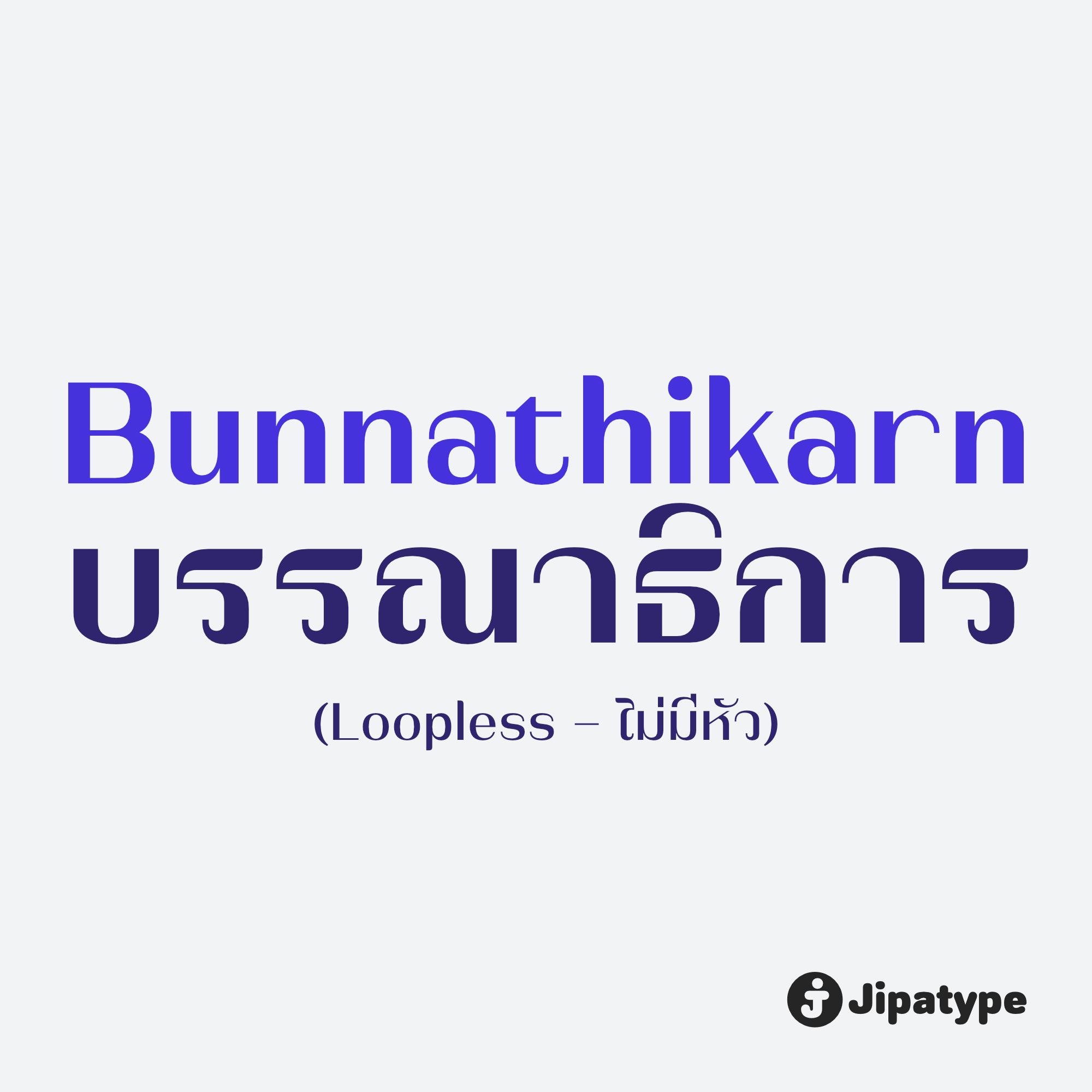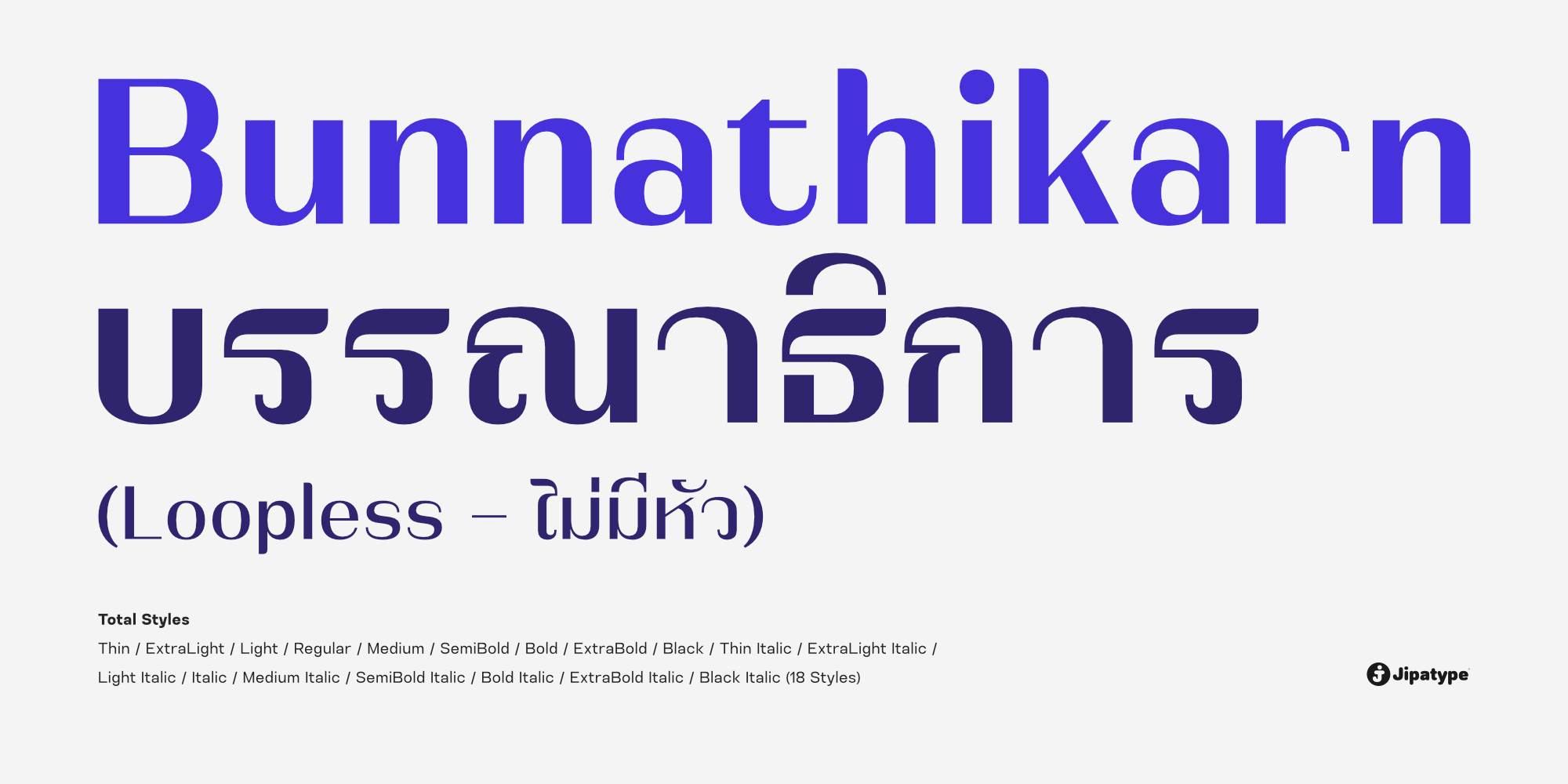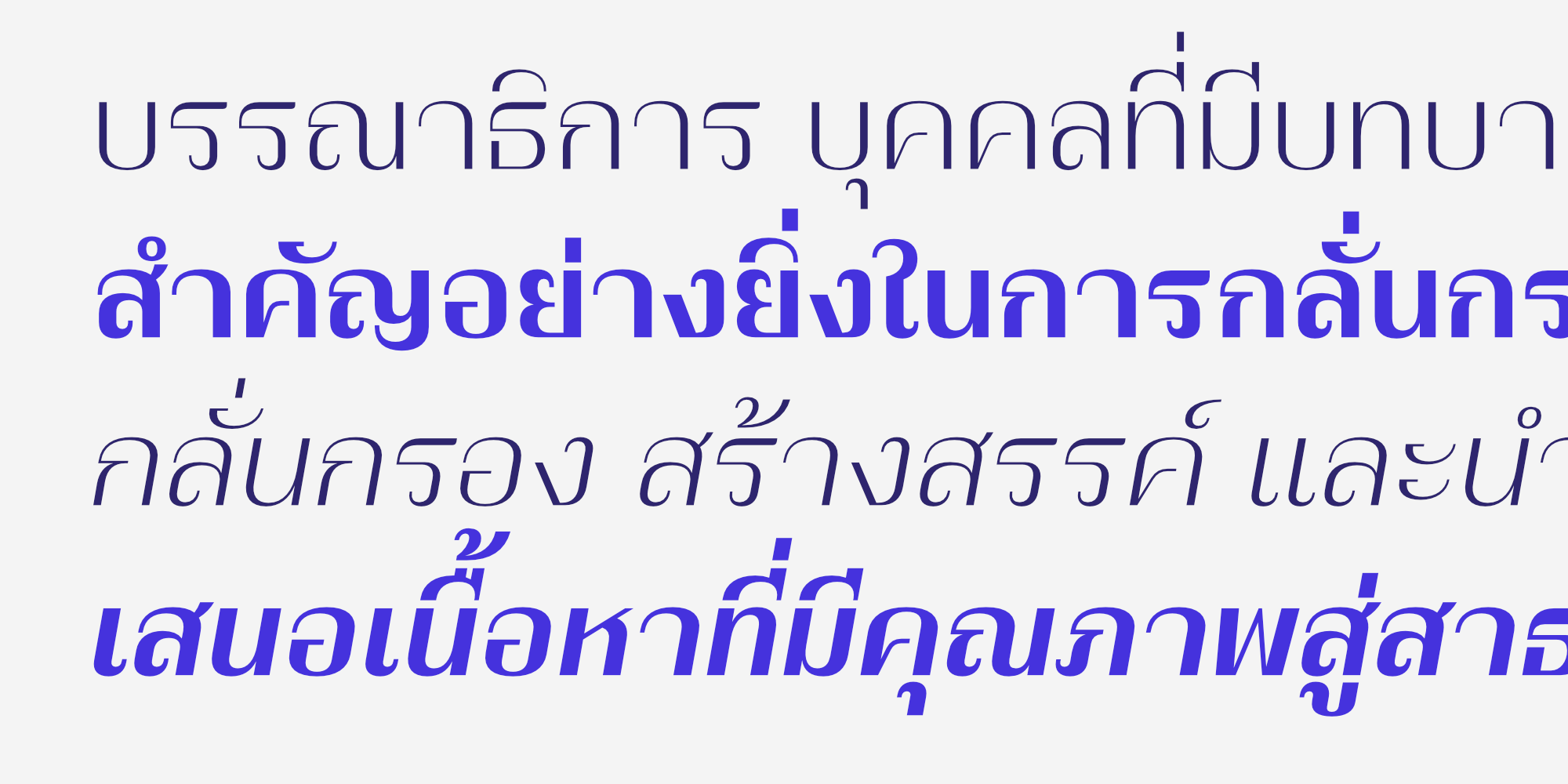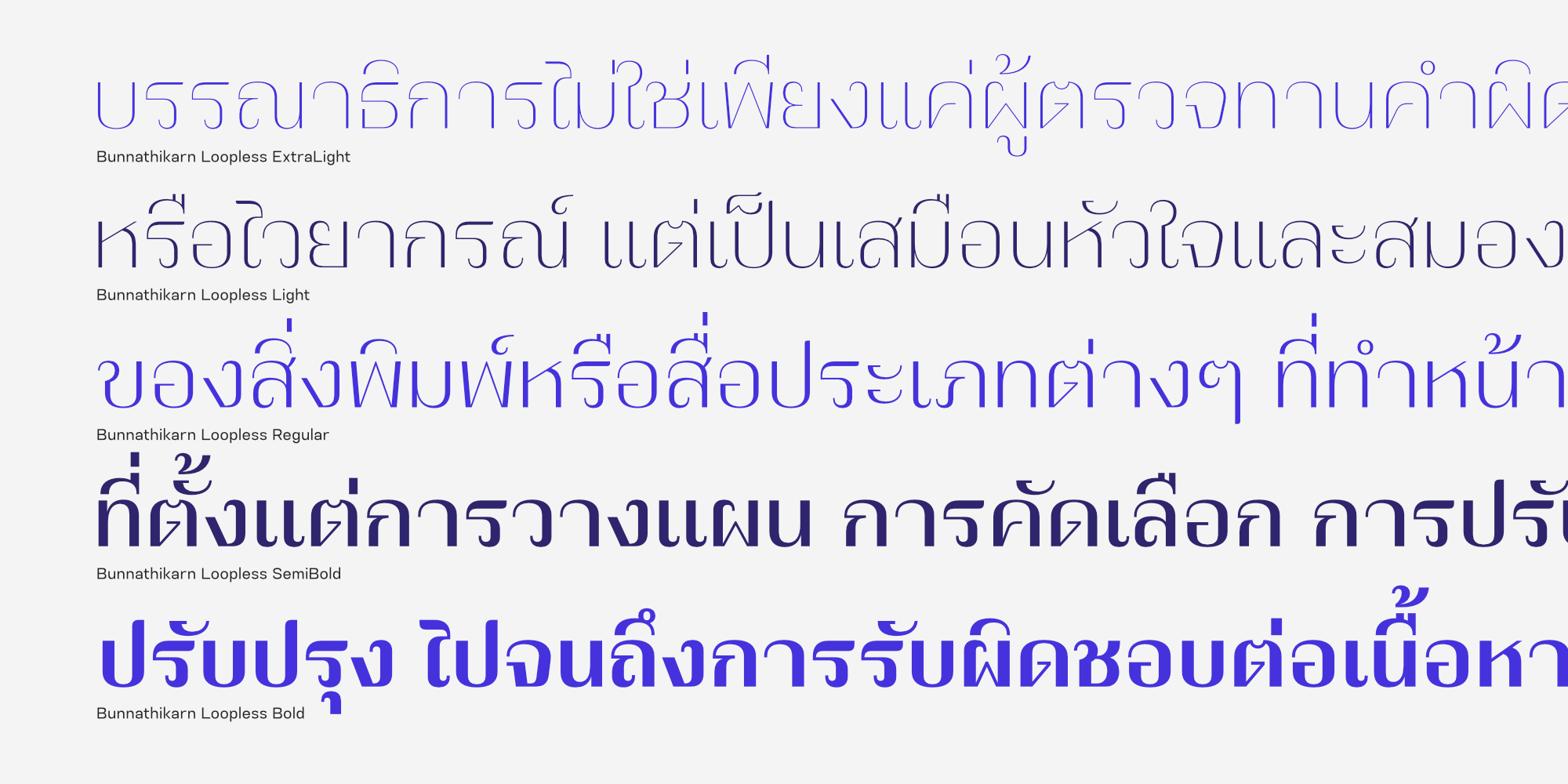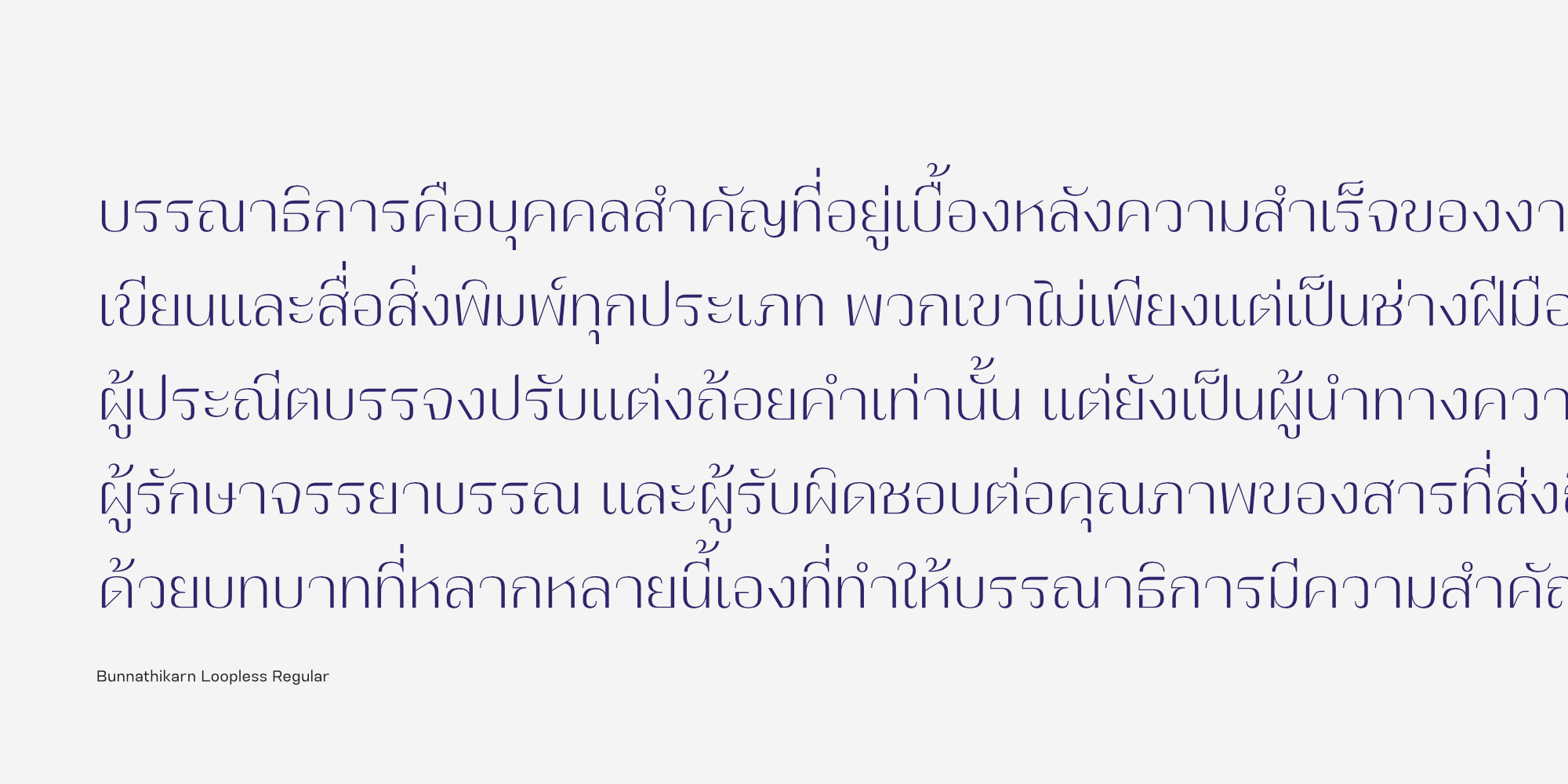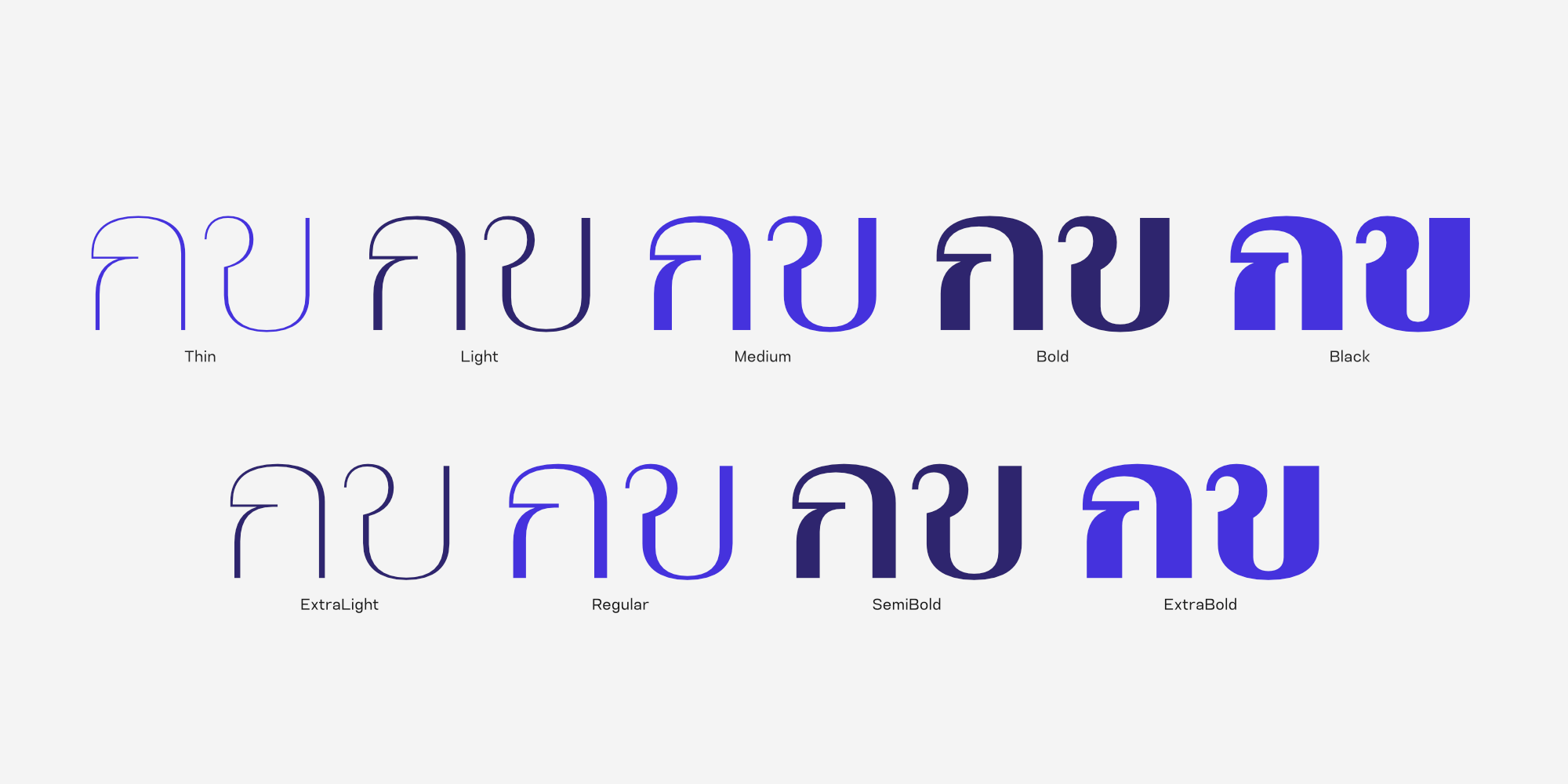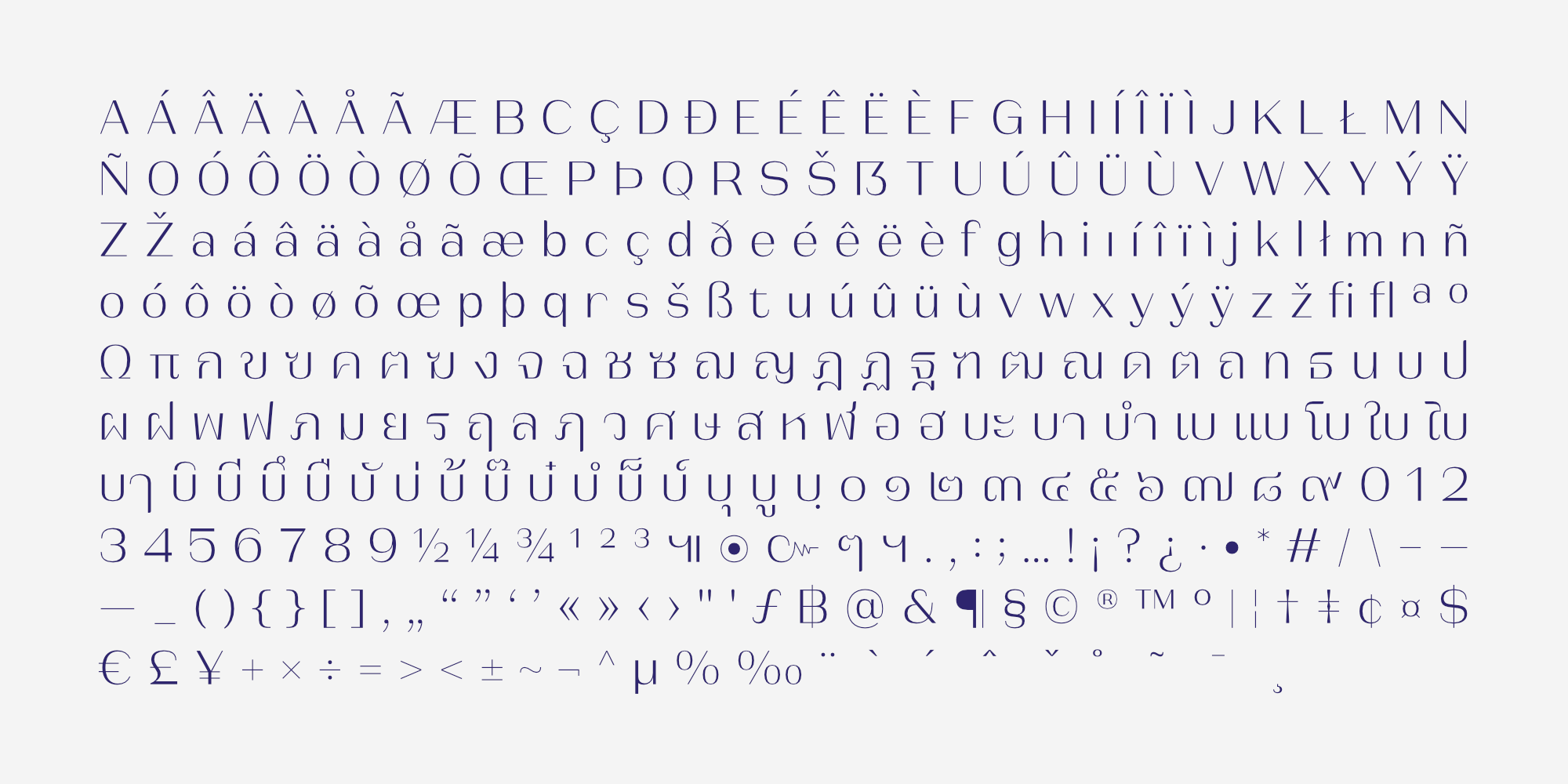
Bunnathikarn Loopless เป็นการต่อยอดดีไซน์จากตระกูล Bunnathikarn โดยปรับเปลี่ยนโครงสร้างอักษรไทยให้เป็นแบบไม่มีหัว เพื่อมอบภาพลักษณ์ที่ดูทันสมัย โฉบเฉี่ยว และมีความเป็นสากลมากยิ่งขึ้น เหมาะอย่างยิ่งสำหรับงานแบรนด์ดิ้งแฟชั่น สินค้าลักชัวรี่ สื่อไลฟ์สไตล์ หรือหัวข้อความ ที่ต้องการสะท้อนรสนิยมที่เหนือระดับและบุคลิกที่มั่นใจ